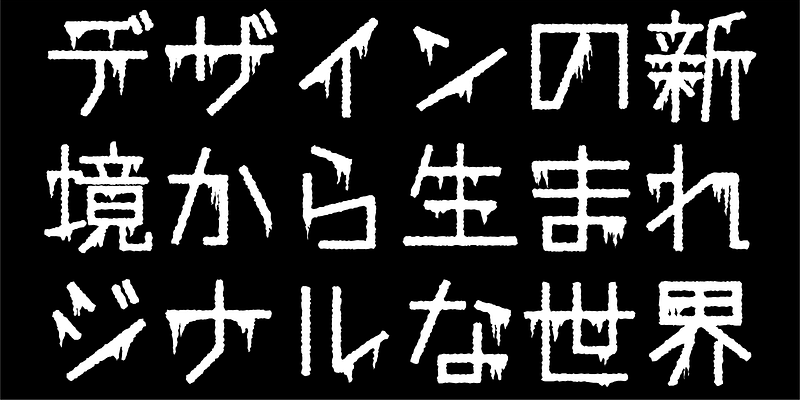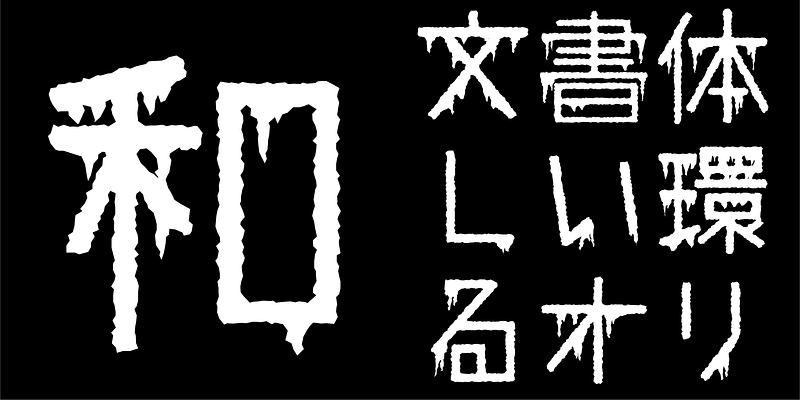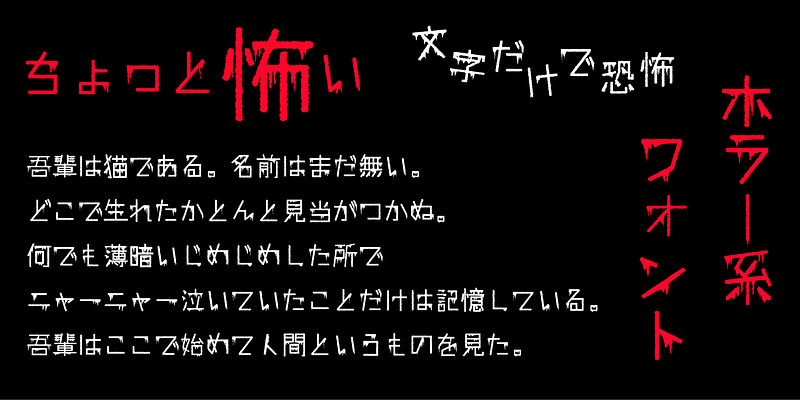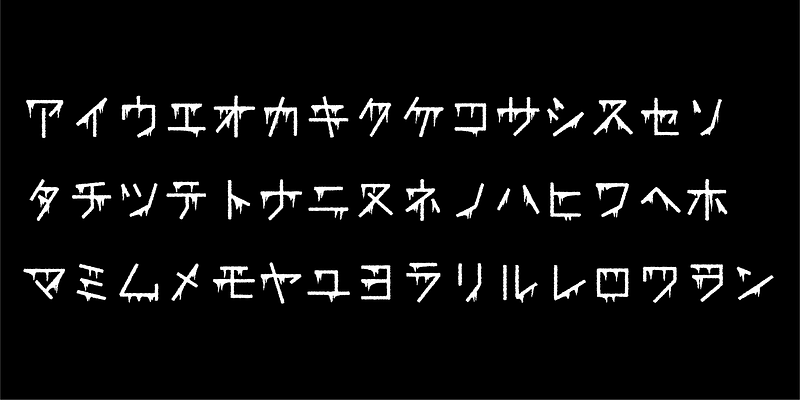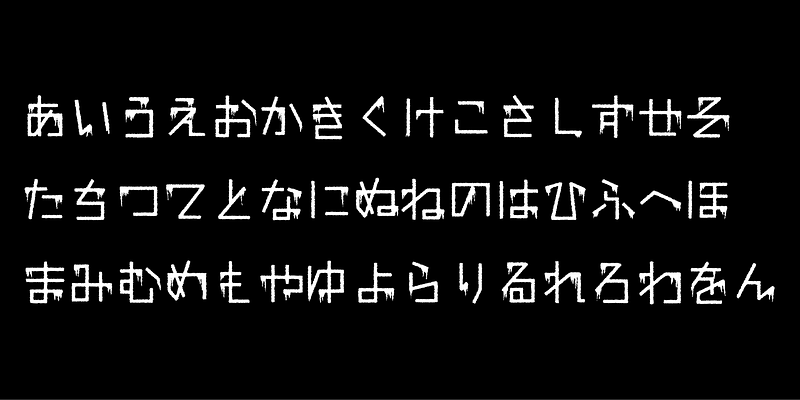
Cette police s’appuie sur Tsurara, l’une des séries de typographies populaires Gradeo, mais ses contours présentent des finitions grossières pour donner un sentiment d’effroi. Elle convient à des fins d’affichage, ainsi que pour le texte superposé dans les clips vidéo.
Ces polices ont été lancées pour la première fois en 1997, avec le logiciel Gradeo pour la création de panneaux et d’affichages.